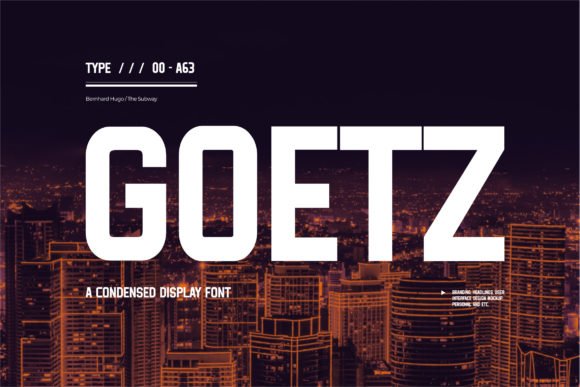
Creativefabrica Goetz Font 2021
[Creativefabrica] Goetz Font (2021)
Goetz - это крутой и толстый шрифт.
Этот шрифт идеально подходит для написания веб-дизайнов, визитных карточек и практически всего, что требует напористости.